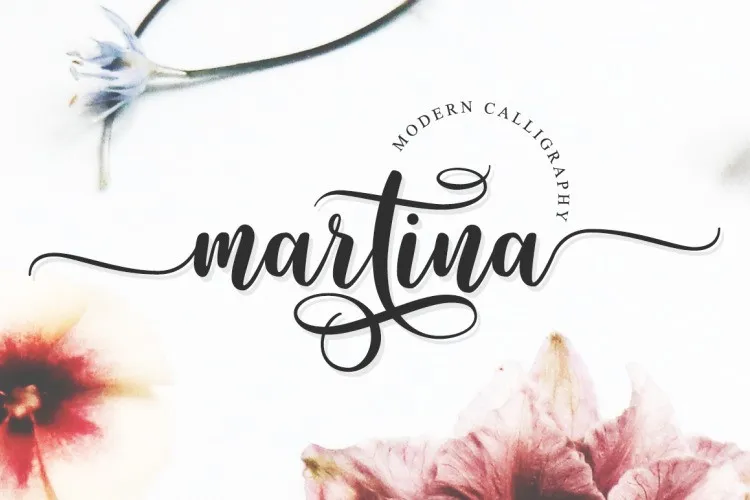
A Martina Calligraphy Font é uma opção perfeita para quem deseja adicionar um toque elegante a seus projetos digitais. Inspirada no traço delicado das mulheres italianas e nas antigas manuscritas, esta fonte de escrita calligrafizada traz uma pegada clássica com um toque sofisticado que certamente encanta. Desenvolvida pelo designer Adhi Nugraha da equipe 0001themes, a Martina é uma opção ideal para aqueles que buscam um estilo contemporâneo e fresh. Esta fonte está disponível em várias linguagens e inclui alternativas de letras para maior versatilidade. Ela se destaca como uma escolha ótima para diversos projetos gráficos, como cartões de convite, cartas de agradecimento, marcadores de produto, camisetas personalizadas, identidades corporativas, logotipos e até mesmo em design de livros ou artes digitais. Com sua simplicidade e beleza, ela pode ser usada tanto com tinta quanto com tinta d’água para criar um visual único e atraente. Estruturada para se encaixar perfeitamente nos mais diversos projetos, a Martina Calligraphy Font é uma fonte que certamente fará sua marca. Ela não apenas adicionará um toque elegante aos seus materiais impressos ou digitais, mas também proporcionará à sua marca ou trabalho de arte um visual único e moderno.